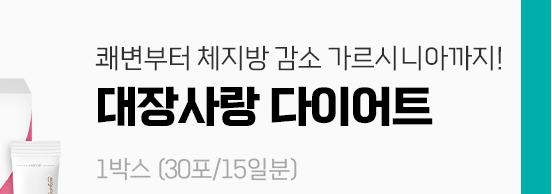
폰트궁금해요ㅜ
큰글씨 작은글씨 못찾겠어요 ㅠ
크고 굵은 글씨는 KOHI배움 같고요 https://www.sandollcloud.com/font/17568.html 작고 얇은 글씨는 더잠실체 같네요 https://www.sandollcloud.com/font/18121.html